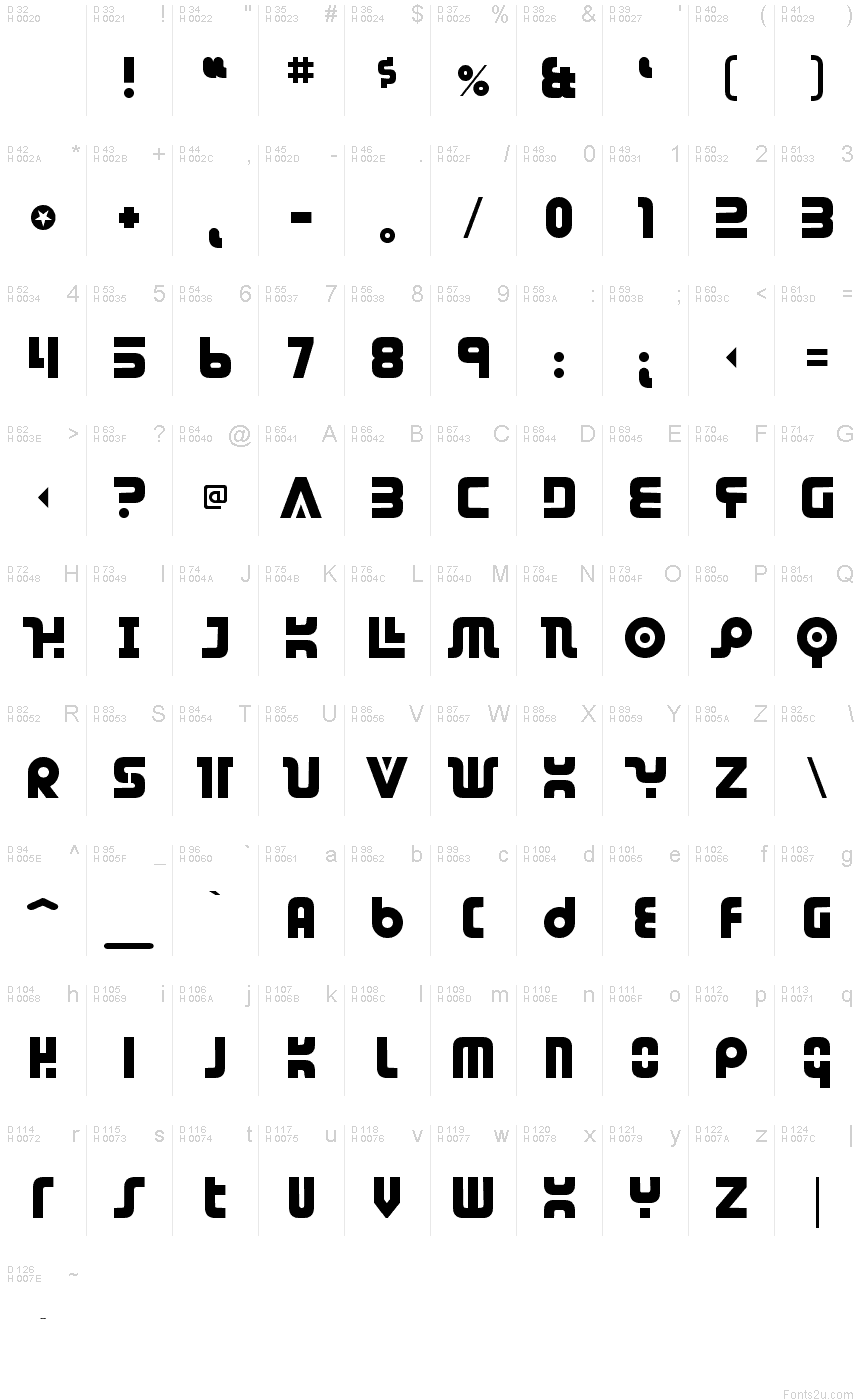
Dendritic Voltage من تصميم Ray Larabie هو خط عرض مستقبلي مجاني، يتميز بأشكال مستديرة ضخمة وإيقاع هندسي دقيق. تمنح الحروف ذات الطابع الموديولي انطباعاً وكأنها نُحتت من قطعة واحدة، مما يضفي على الشعارات والعناوين حضوراً انسيابياً وكهربائياً يلفت الأنظار من النظرة الأولى.
يتألق هذا الخط المجاني في شعارات الخيال العلمي، وعناوين الألعاب، وملصقات التكنولوجيا، وأغلفة الموسيقى الإلكترونية، ورؤوس صفحات واجهات المستخدم، ومنشورات الفعاليات، ورسومات يوتيوب الجريئة. استخدم Dendritic Voltage بأحجام كبيرة لإبراز منحنياته السميكة وتداخلاته الدقيقة؛ وللنص الأساسي، قم بدمجه مع خط بسيط بلا زوائد (Sans-Serif) للحفاظ على نظافة التصميم وسهولة القراءة.